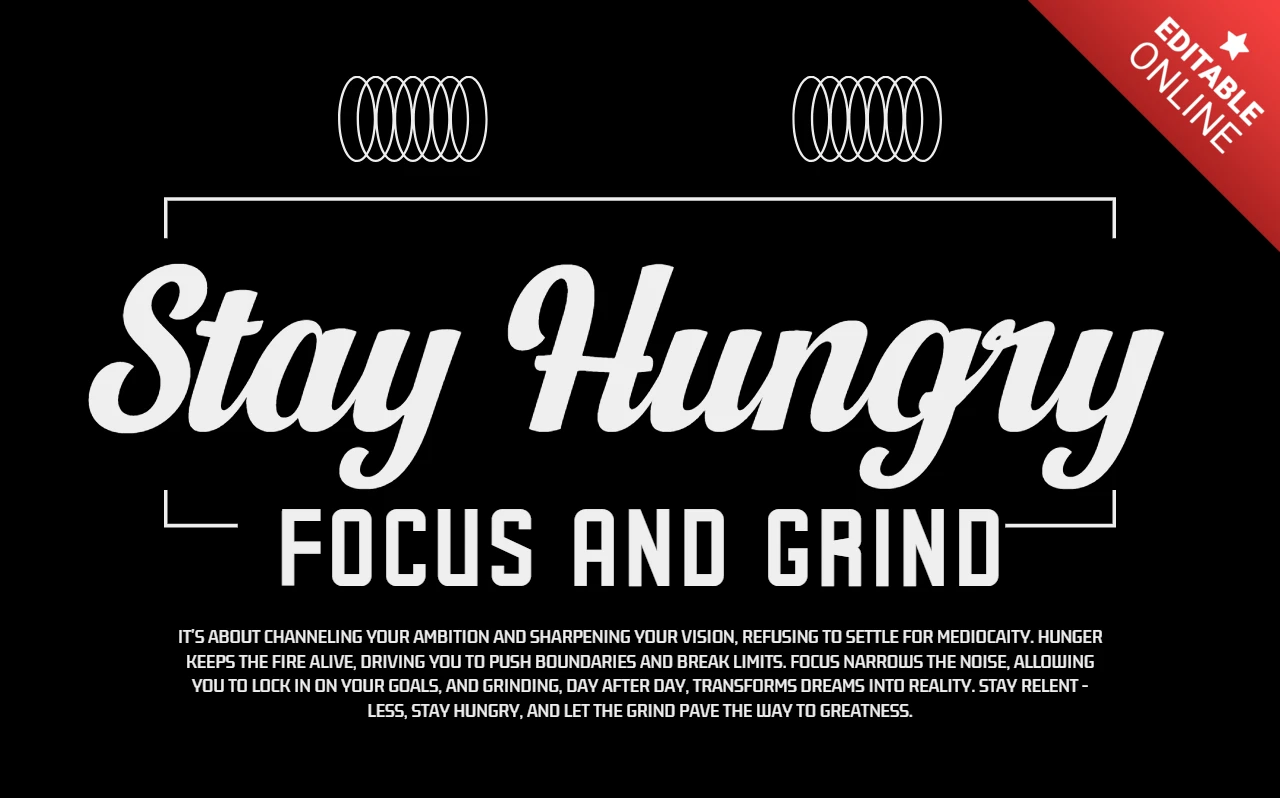
Modèle de conception de citation motivante pour des affiches avec une typographie audacieuse
Éditer dans Design Studio Télécharger en JPGÉlevez votre marque avec notre modèle de design moderne, mettant en avant une typographie audacieuse et des slogans inspirants—parfait pour les vêtements de rue, les produits dérivés et les affiches motivantes qui incarnent la détermination et l'effort.